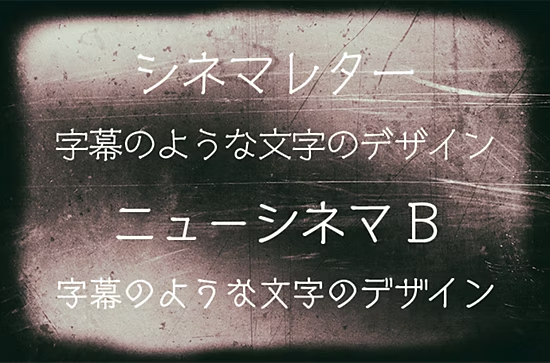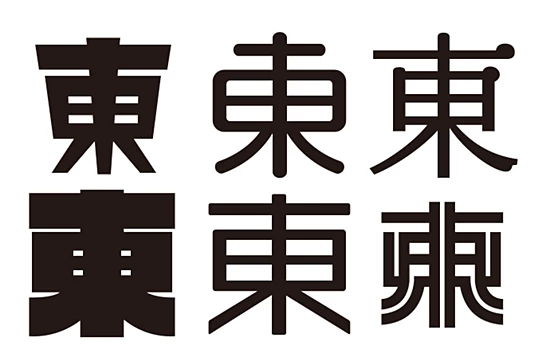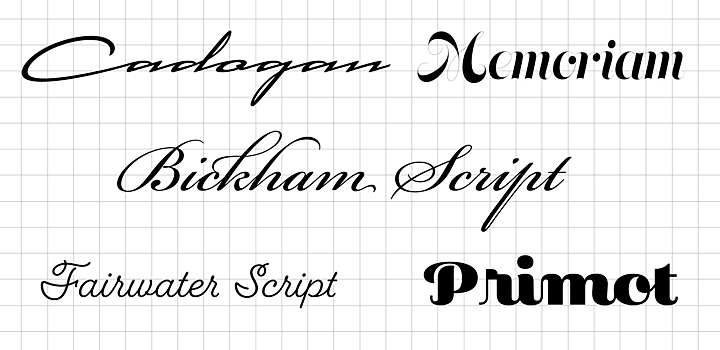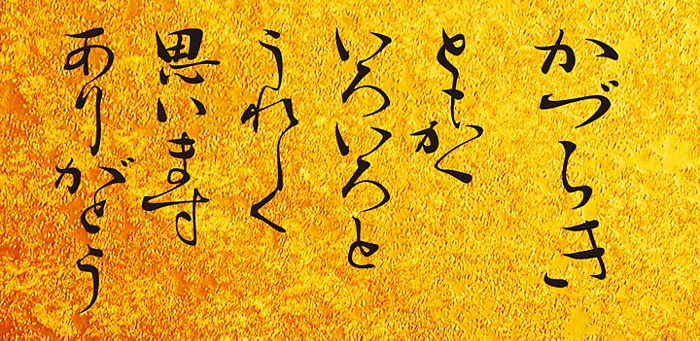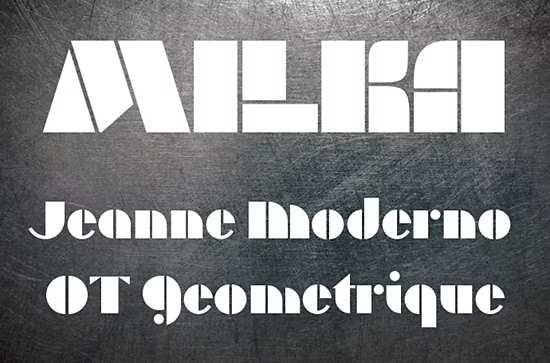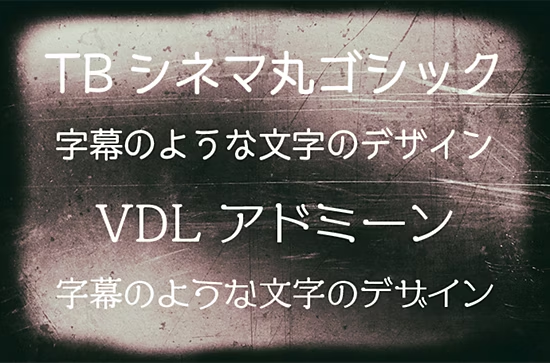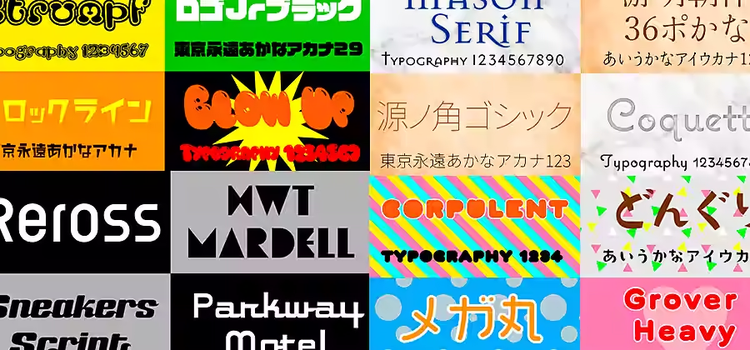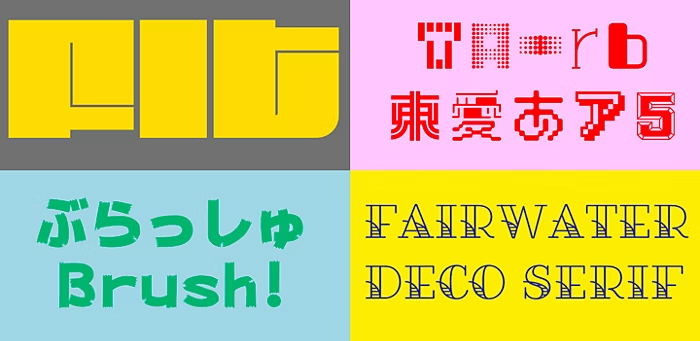
表現力豊かなデザインフォントの世界
本、新聞、ポスター、看板、そしてパソコンやスマートフォン……私たちは日々、文字に触れていますが、その文字のかたちは実に多種多様です。同様にそのデザインされた文字のセット「フォント」も非常に多くの種類があります。ここではスクリプト・筆記体・手書き系フォント、毛筆・筆文字フォント、ステンシル・字幕風フォントといった、特徴的なデザインのフォントを紹介していきます。
デザインフォントとは?
「デザインフォント」という言葉はフォントを分類する際によく使われる言葉ではありますが、「こういうものがデザインフォント」という、正確な決まりがあるわけではありません。
明朝体であれば「横画が細く、縦画が太い」「ウロコと呼ばれる▲状のおさえがある」、ゴシック体であれば「横画と縦画が近い太さ」、丸ゴシック体であれば「横画と縦画が近い太さで先端が丸い」といった特徴がありますし、楷書体、行書体、草書体、隷書体といった伝統的なフォントは、それぞれの書風にならった特徴を備えています。
明朝体/ゴシック体/楷書体フォント
デザインフォント
「デザインフォント」は、こうしたフォントの分類に属さないフォントの総称と言うことができるでしょう。
デザインフォントの中には、個性的なデザインのものもあれば、明朝体風デザインフォント、ゴシック体風デザインフォントもあり、その種類は膨大です。
しかし、いくつか表現手法としてカテゴライズされているものもあるので、ここではAdobe Fontsで使えるフォントの中から、そうしたデザインフォントを紹介していきます。
スクリプト・手書き系フォント
スクリプトフォントとはいわゆる筆記体の欧文フォントのことを指します。カリグラフィーのように伸びやかで優美な装飾を備えるものから、スピード感あふれるデザイン、手書きの風合いのあるものまで、さまざまなデザインがあります。欧文のカリグラフィックなスクリプトフォントは日本のデザインにおいても高級感、優雅さを演出したいときによく使われています。
Cadogan/Memoriam/Bickham Script/Fairwater Script/Primot
日本語フォントにおけるスクリプトフォント・筆記体フォントを、手書きの文字をベースにしたものと置き換えるならば、楷書・行書・行書等の筆書体フォントや、手書き風フォントがこれにあたると言えます。筆書体フォントはフォーマル、伝統、格式を表現したいときによく使われますが、手書き風の日本語フォントはやさしさ、温かみ、親近感を出したいときに使われています。
筆記用具によって書かれる文字の表情が異なるように、スクリプト・手書き風フォントもそれが何で書かれた文字を元に作られたものかによって、文字のデザインは大きく変わります。日本語フォントにも、筆で書かれた文字のほか、鉛筆、マーカー、万年筆などを使ったフォントがリリースされており、文字のかたちもニュートラルなものから個性的なものまでいろいろなものがあります。
ペンジェントル/ペンレディ/クレー/Nothing/Verveine/P22 Cezanne
毛筆フォント・筆文字フォント
毛筆フォント・筆文字とは、おもに筆で書かれた日本語フォントのことを指します。
前述の楷書体、行書体、草書体、隷書体のような伝統的な筆書体フォントのほか、歌舞伎の看板や筋書に使われる勘亭流、相撲の番付等に使われる相撲文字、千社札や提灯の文字などに使われる籠文字等々、さまざまなフォントがあります(こうした伝統的な筆書体として扱われ、「デザインフォント」には分類されないケースが多いと言えますが、筆法や骨格を取り入れつつ、文字のかたちや画線の処理を変えたものもあり、筆書体フォントとデザインフォントを正確に分けるのは困難です)。
日活正楷書体
香蘭
このほか、近年ではこうした伝統的な書法によらず、よりデザイン性、創作性、オリジナリティを重視した筆文字・毛筆フォントも出てきており、これまでの毛筆フォント=伝統的、格式が高い、フォーマルという印象だけでなく、多様な表現ができるようになっています。
また、OpenTypeフォントの技術を活用し、正方形の中に一文字一文字を収める日本語フォントの枠組みにとらわれることなく、次の文字とつながるような文字表現を可能にする、連綿体の文字を収録したフォントも登場しています。こうした動きは従来の活字から連なる日本語フォントの設計からの脱却という点で非常に興味深い流れと言えるでしょう。
かづらき
ステンシル・字幕風フォント
ステンシル風フォントとは、おもに欧文フォントに見られる閉じた部分のないデザインのフォントのことで、たとえば「O」の文字でも「( )」のように、上下の線が途切れているところがあるのが特徴です。
Rufina Stencil/Stenciletta
Milka/Jeanne Moderno OT Geometrique
ステンシルとは、文字や模様のかたちに切り抜かれたテンプレートをなぞったり、スプレーで塗ることによって印字するもので、製図や屋外で使われています。ステンシル風フォントはこのテンプレートの文字の特徴を活かして作られています。
“文字の線に途切れた部分がある”という特徴を持つフォントは日本語フォントにもあります。
それが「シネマレター」(モリサワ)や「ニューシネマB」(フォントワークス)のような字幕風フォントです。シネマフォントとも呼ばれ、昔の映画の字幕のような独特の丸みと、読みやすさを備えています。
なお、ステンシル風フォント同様とは異なり、完全に閉じた部分がないというわけではなく、字幕文字のようなかたちを持つデザインフォントもあります。
シネマレター(モリサワ)/ニューシネマB(フォントワークス)
TBシネマ丸ゴシック/VDLアドミーン
まだまだたくさん!デザインフォントの世界
ここで紹介したフォント以外にも、分類ができないようなユニークなデザインフォントはたくさんあります。